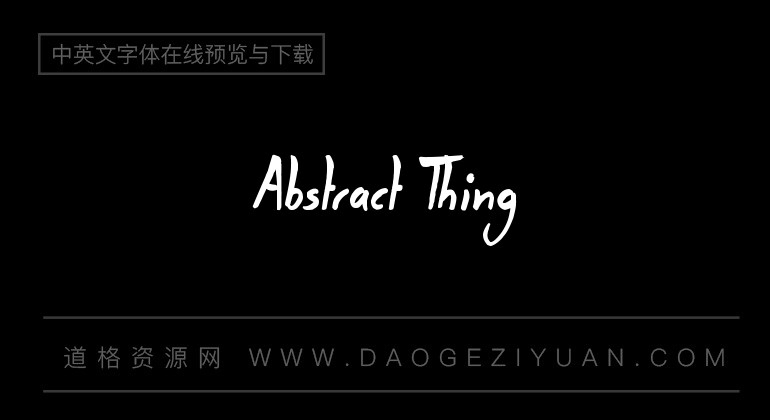
? Abstract Thing 字体是一种抽象风格的字体,它以抽象的图形和抽象的形状来表达文字。它的特点是抽象的形状,细节,色彩和字体结构,使得它能够给文字增添独特的视觉效果。Abstract Thing 字体可以用来创建有趣的标题,标签和海报,以及用于品牌和商标的设计。内容介绍
Abstract Thing是一款非常不错的手写艺术字体,具有很好的视觉感,适合于文化类的宣传设计、商业类品牌的广告和产品包装设计以及个性化文字排版等较多场景。